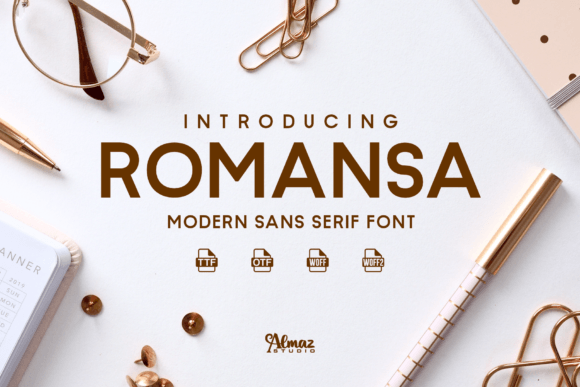
Romansa
Romansa: A Fonte Elegante que Transforma Qualquer Projeto
Se você está em busca de uma tipografia que una sofisticação e personalidade, Romansa chegou para ser a escolha perfeita. Essa nova família tipográfica oferece muito mais que letras bonitas – ela entrega característica visual forte que destaca posters, gráficos de jogos, camisetas, vídeos, sinalizações, e‑books, logotipos e muito mais.
Por que Romansa se destaca?
- Versatilidade incomparável: múltiplas alternativas de estilo dentro da mesma família permitem criar desde títulos impactantes até textos de corpo legíveis.
- Detalhes que encantam: os terminais levemente curvados para dentro dão à fonte um toque amigável e distintivo, perfeito para marcas que buscam personalidade.
- Design robusto: traços fortes e bem definidos garantem ótima legibilidade em diferentes tamanhos, seja em um cartaz de rua ou em um ícone de aplicativo.
- Ideal para branding: use Romansa em logotipos, badges e capas de revistas para transmitir confiança e elegância ao mesmo tempo.
Aplicações práticas que você pode explorar
Com Romansa, as possibilidades são quase infinitas:
- Criação de posters promocionais que chamam a atenção nas vitrines.
- Desenvolvimento de gráficos para games com um visual moderno e atraente.
- Design de camisetas e merchandise com tipografia que se destaca nas cores.
- Produção de vídeos e animações onde o texto precisa ser claro e impactante.
- Elaboração de e‑books e documentos digitais que combinam leitura confortável com estética premium.
- Construção de logotipos e identidade visual para startups e marcas estabelecidas.
Conclusão: A escolha certa para quem quer se diferenciar
Romansa não é apenas mais uma fonte – ela é um aliado estratégico para designers que desejam criar projetos únicos e memoráveis. Seu design robusto, aliado aos detalhes sutis dos terminais, garante que sua comunicação visual se destaque em qualquer plataforma. Experimente Romansa hoje mesmo e descubra como uma tipografia pode transformar a percepção da sua marca.